【完全版】王道4大番組を完全再現!Premiere Proテロップ コンプリートセット(第1〜4弾Remaster)(‼️有料フォント別購入推奨‼️)
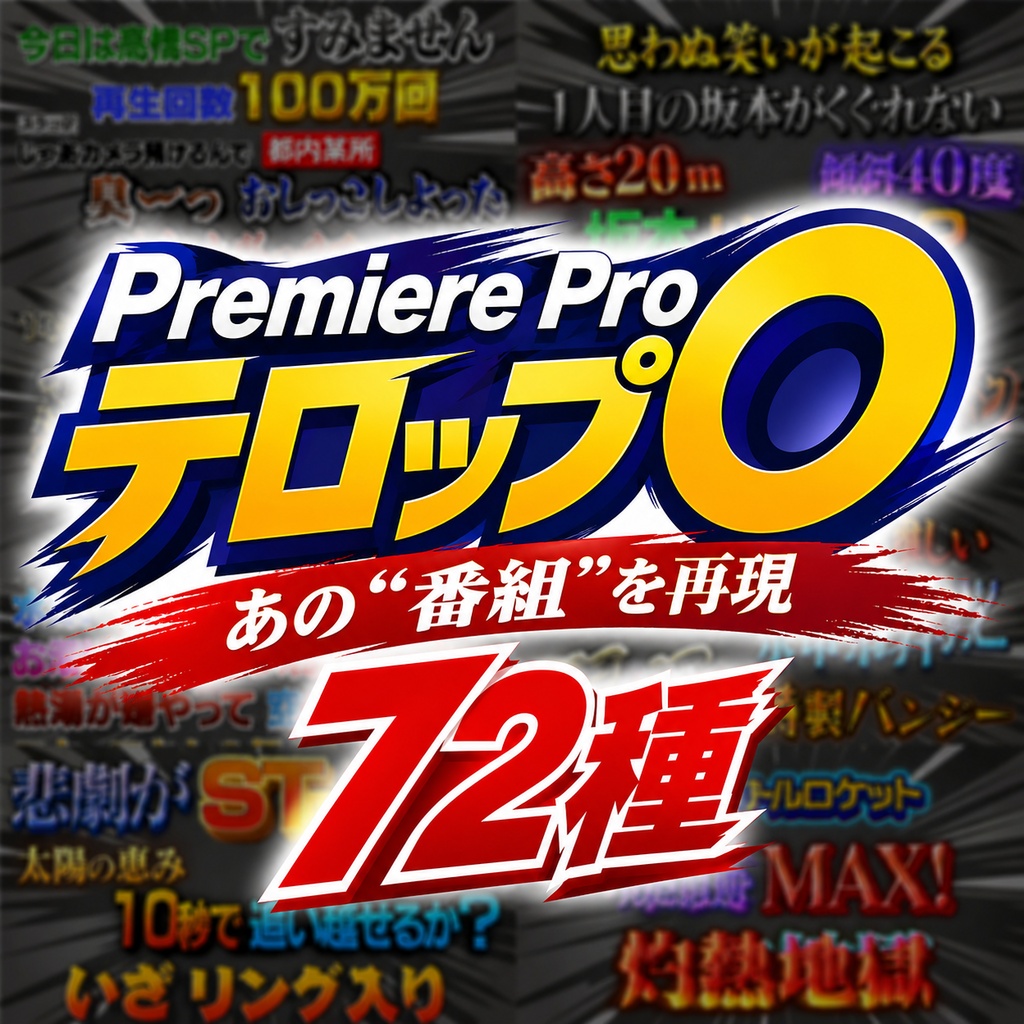
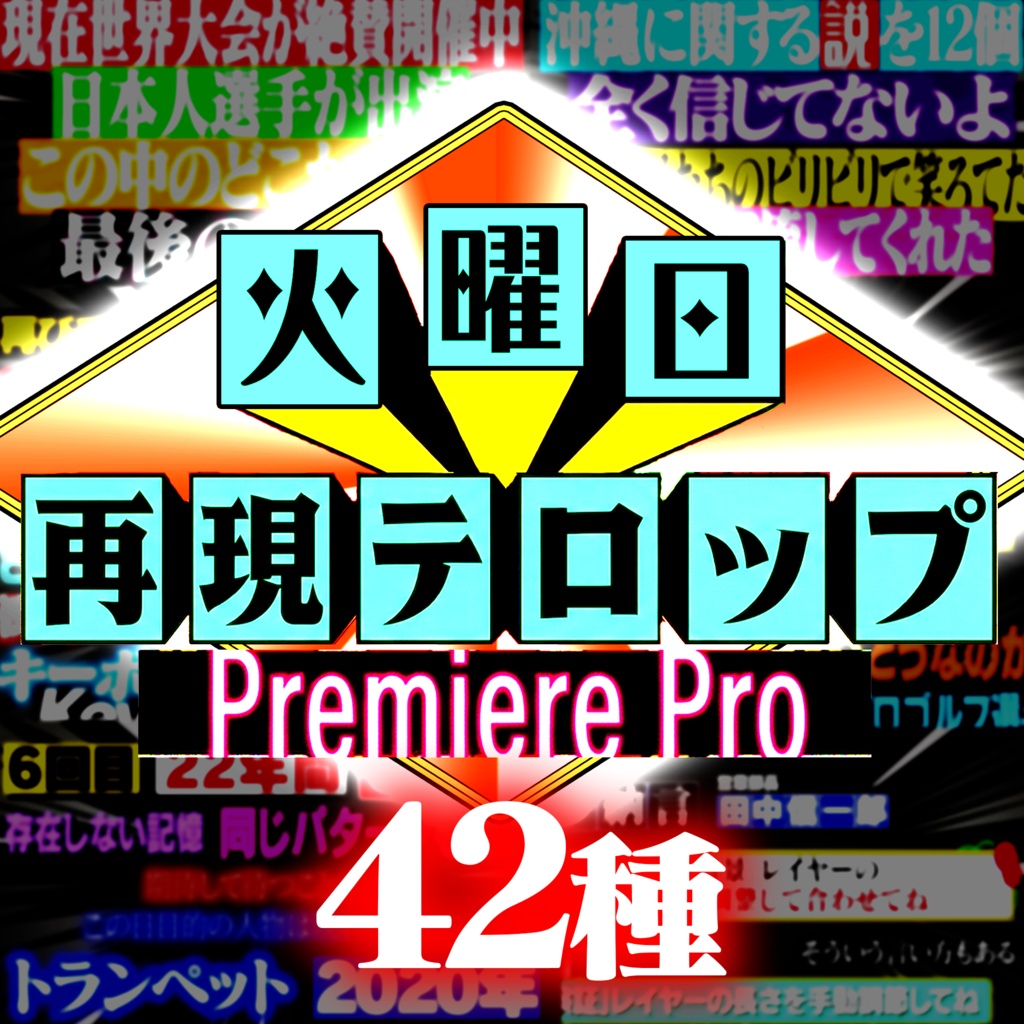
\ YouTubeでバズる「最強の企画」が、これ一つで全て作れる! / 当ショップの大人気『Remaster(完全版)シリーズ』第1弾〜第4弾を、全て網羅した究極のコンプリートセットが遂に登場! 「検証・説」「外ロケ・冒険」「街頭インタビュー・素人イジリ」「高級品 vs 安物の対決」。 YouTubeで最も数字が取れる【4大王道企画】のテロップが、過去最大ボリュームの【全289種類】収録されています。 テレビ局さながらの「圧倒的な光沢感」「重厚な3D立体感」を極限まで追求したプロ仕様の超・高画質テンプレートです。 【収録内容(全289種)】 📺 第1弾 Remaster(検証・説番組風):42種 明朝体の鋭いツッコミや、黒板風フリップなど、検証企画に必須のフォーマット! 📺 第2弾 Remaster(冒険バラエティ風):72種 ポップな状況説明やカラフルな装飾で、ロケ動画やゲーム実況を最高に盛り上げる! 📺 第3弾 Remaster(深夜バラエティ風):102種 過去最多ボリューム!ピンクや紫の毒舌ツッコミで、素人イジリやトーク動画がプロ級に! 📺 第4弾 Remaster(お正月特番・格付け風):73種 金・銀の豪華絢爛な3Dテロップ!「一流・三流」の対決や高級品レビュー企画に!
フォントに関する注意事項
本テンプレートではフォントワークスやAdobe CCなどで購入できる有料フォントを使用しているため、添付画像を完全に再現するにはそれらの導入が必要です。ただし、似ている無料フォントによる代替案も併せて紹介いたします。 【使用している有料フォント】 ニューロダン系 FOT-ニューロダン Pro(B / DB / EB / UB) FOT-ニューロダン ProN(B / EB) マティス系 FOT-マティス ProN(L / DB / EB / UB) マティスみのりやまとPro(EB) FOT-マティスえれがんと Pro(EB) その他 FOT系 FOT-ロダンNTLG Pro(EB / UB) FOT-スランプ Std(DB) FOT-ユールカ Std(UB) FOT-ロウディ Std(EB) FOT-古今江戸 Std(EB) FOT-花風テクノ Std(U) FOT-ニューシネマA Std HOT・その他のメーカー系 HOT-大髭113 Std(H) HOT-忍者 Std RoG2サンセリフStd(B) レゲエ One ダイナフォント系 DFP超極太楷書体 DFP極太楷書体 DFGロマン雪 W9 【使用している無料フォント】 HGP創英角ポップ体 【無料フォント代替案】 マティス ProN EB → 源ノ明朝 ニューロダン → ヒラギノ角ゴ